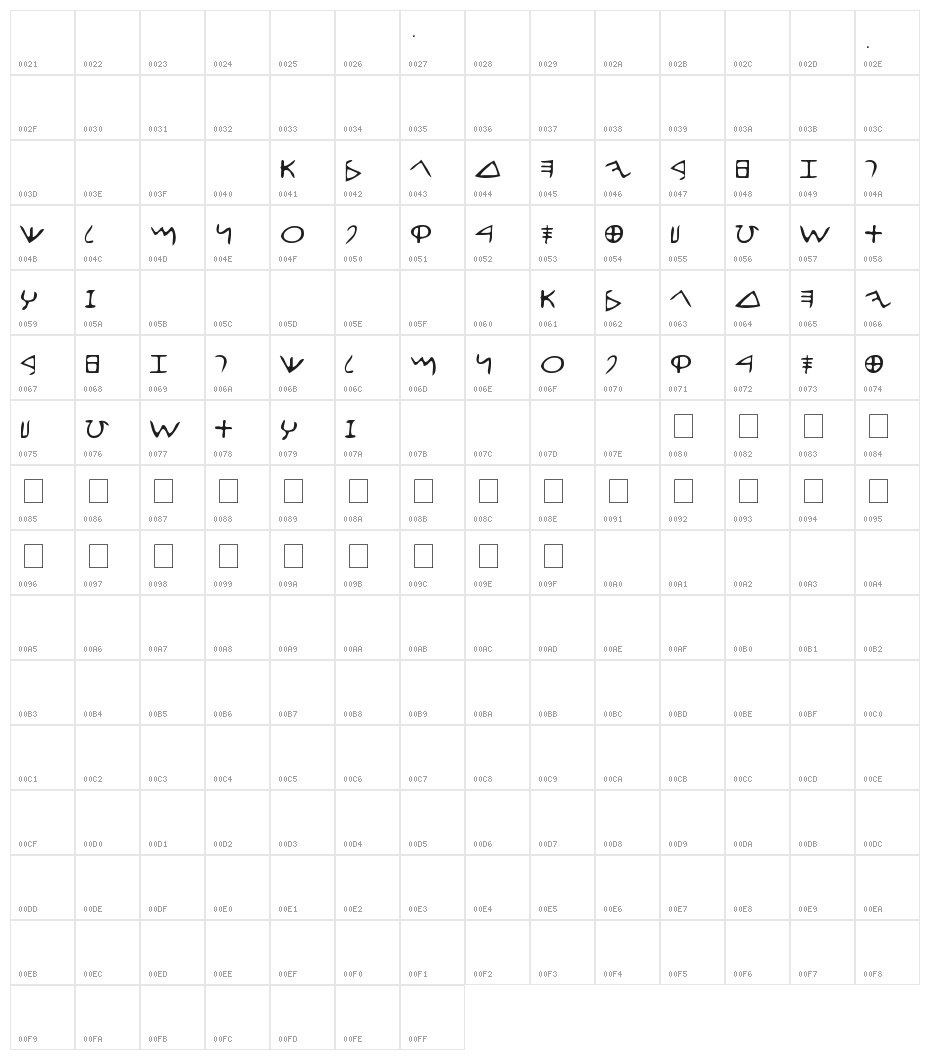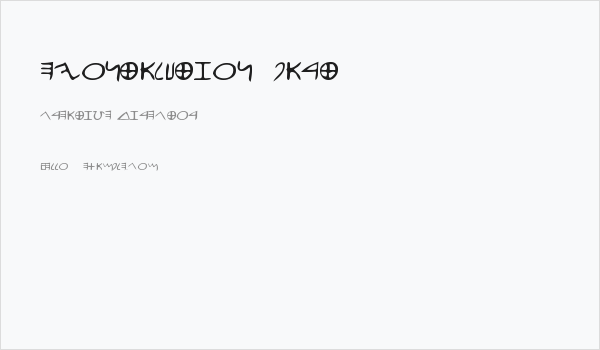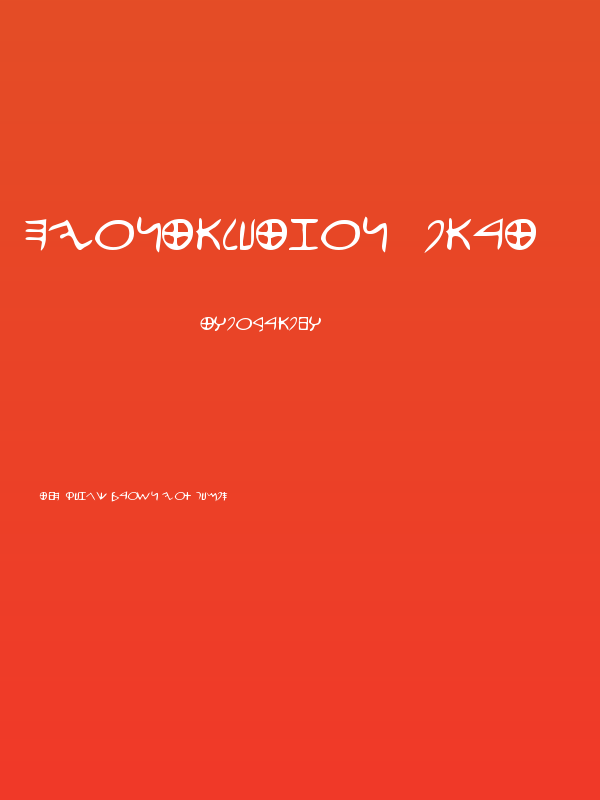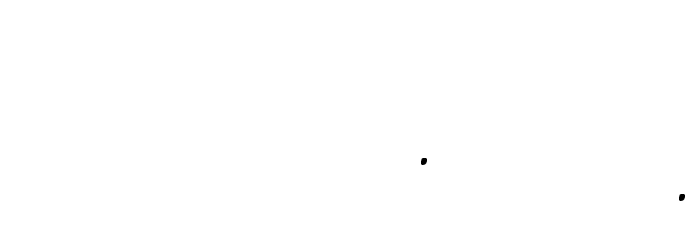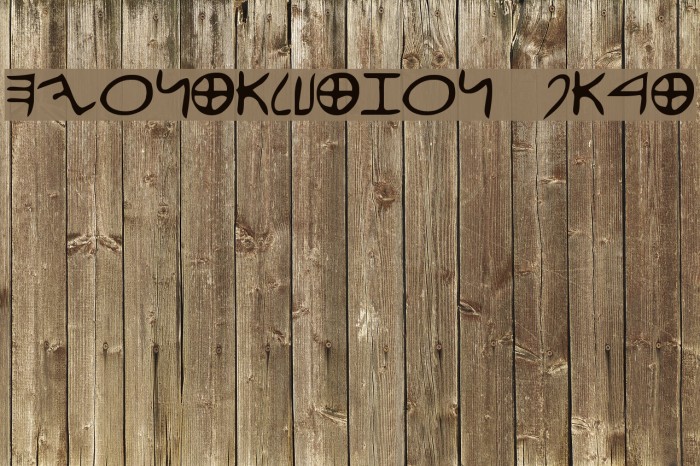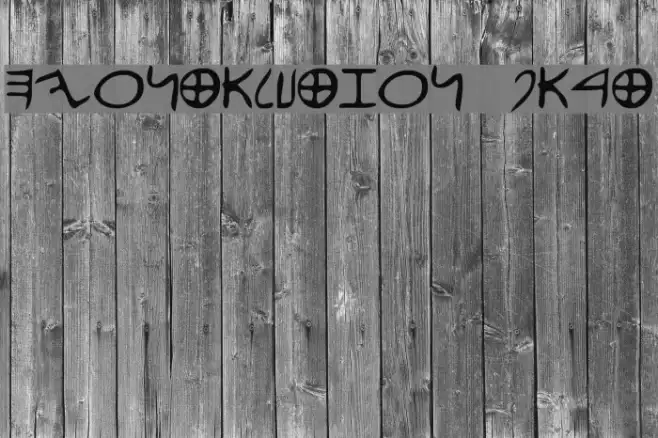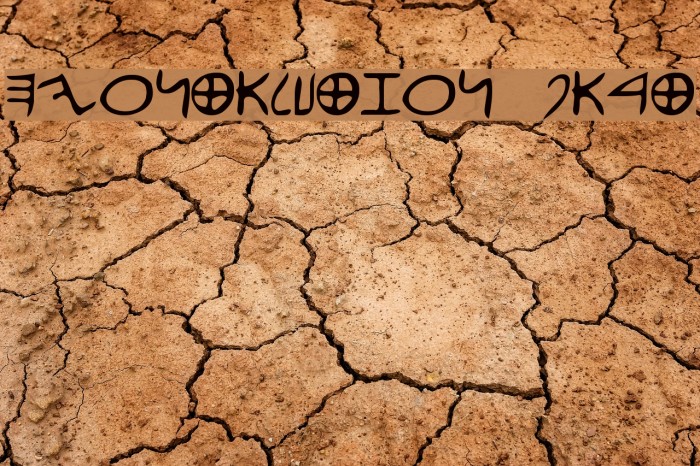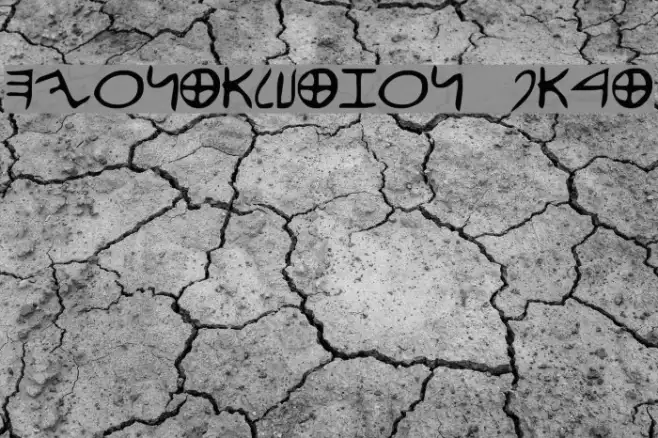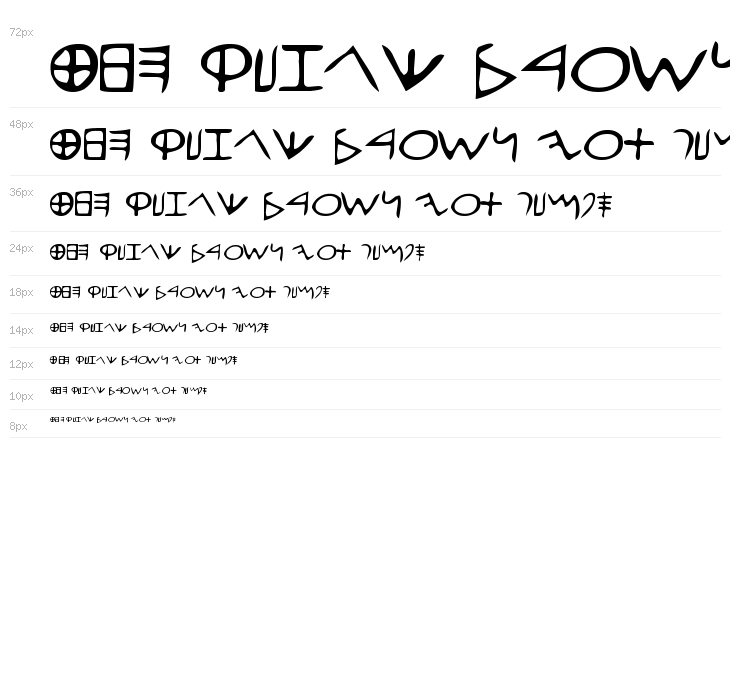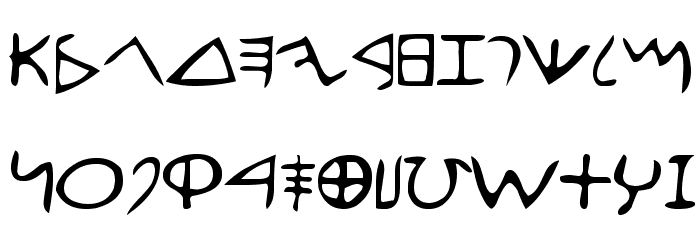
efontalution_part1 Font
| Stile generale | Modern, Artistic |
| Caso d'uso | Logos, Posters, Creative Projects |
| Progetti proposti | Ideal for fantasy-themed designs, artistic projects, or branding that requires a mysterious and unique touch. |